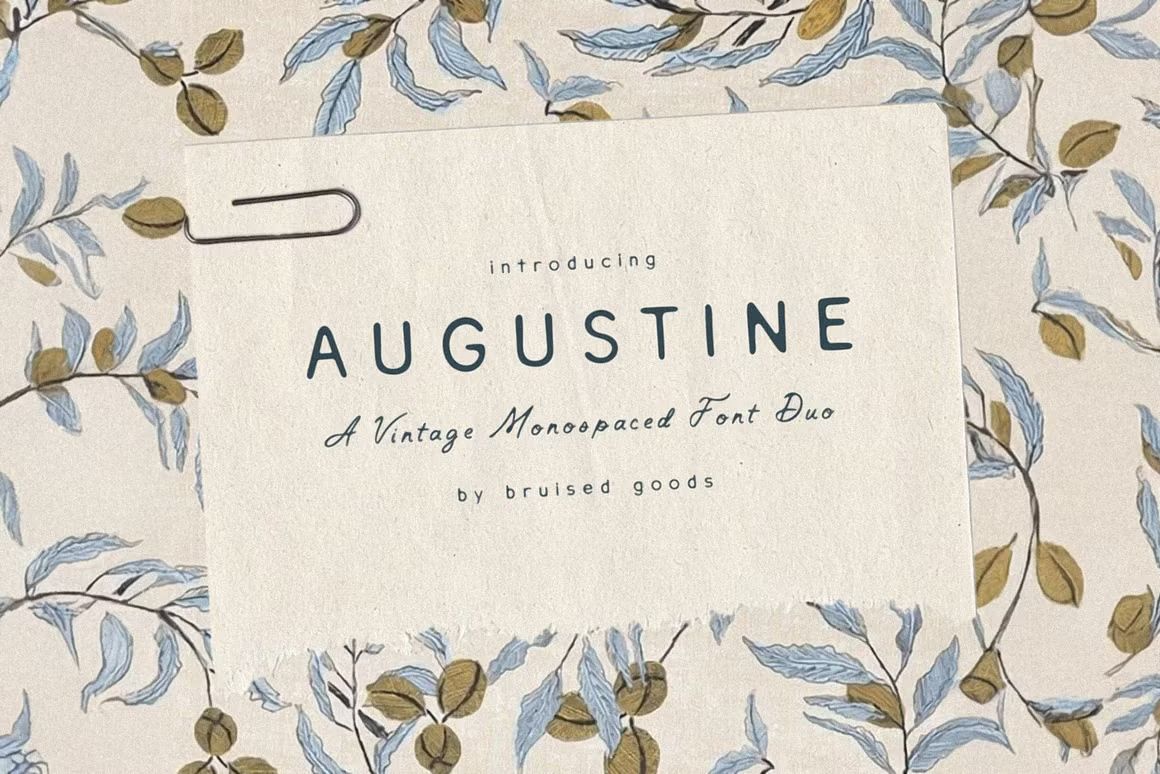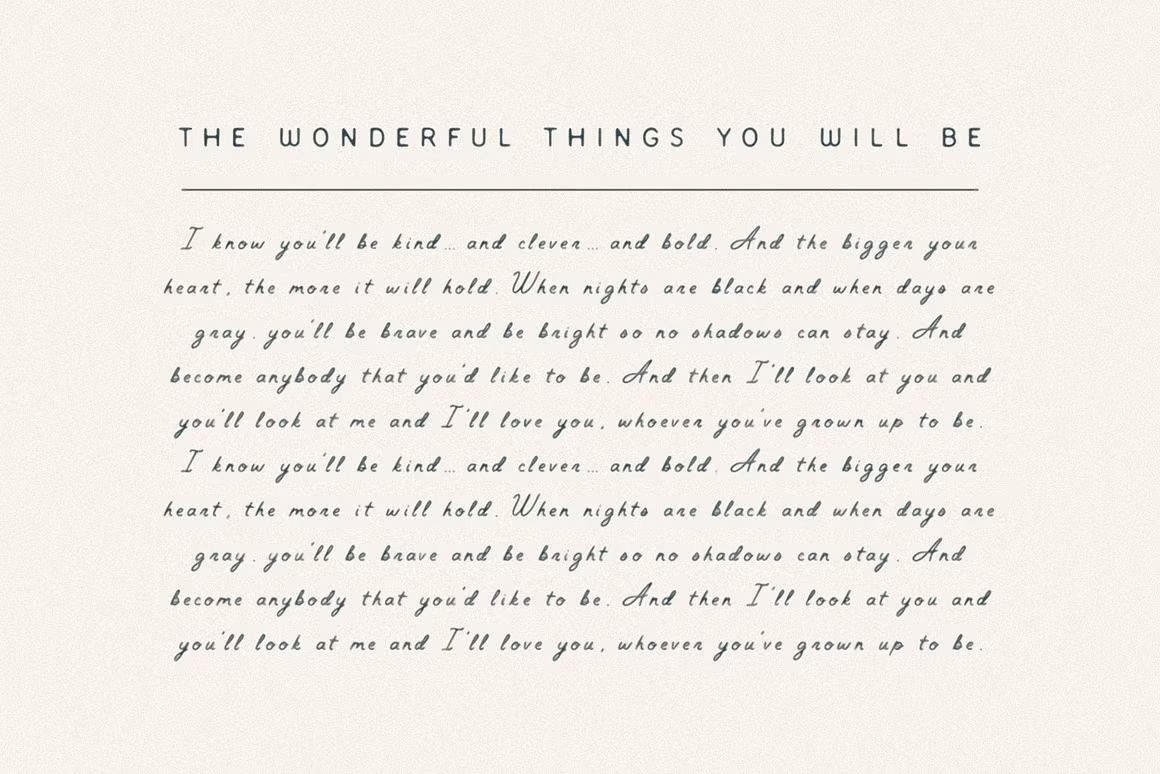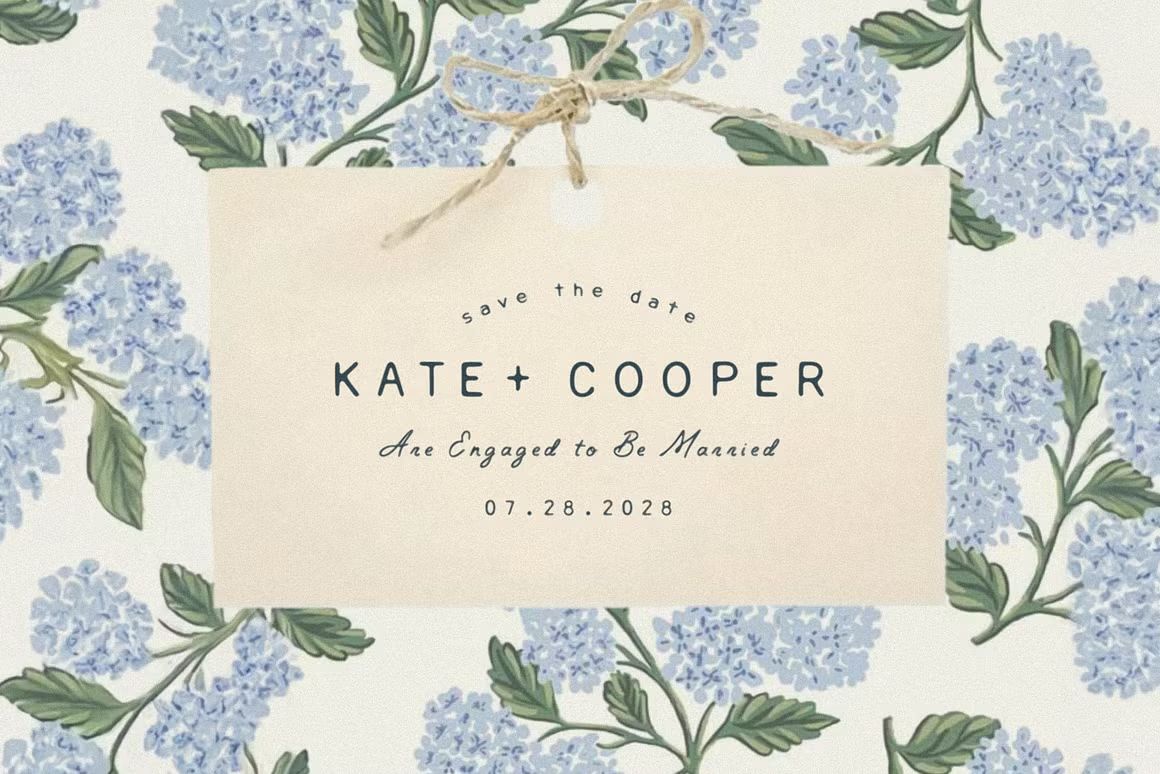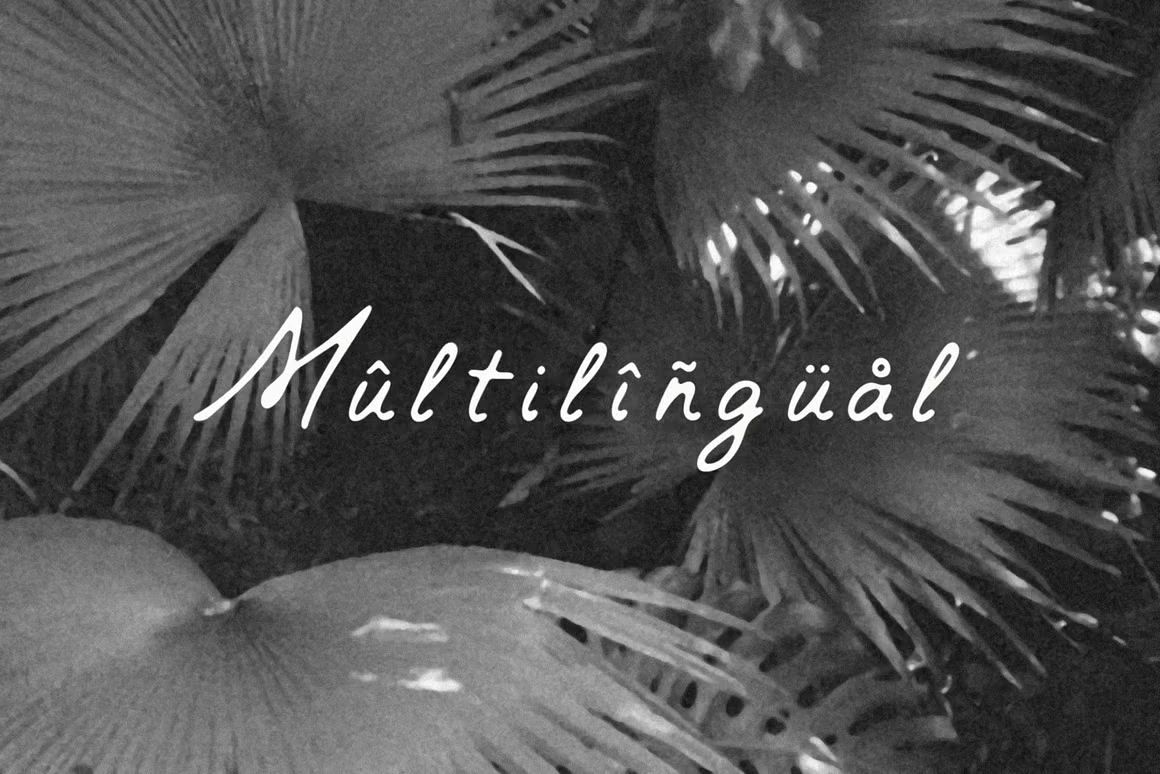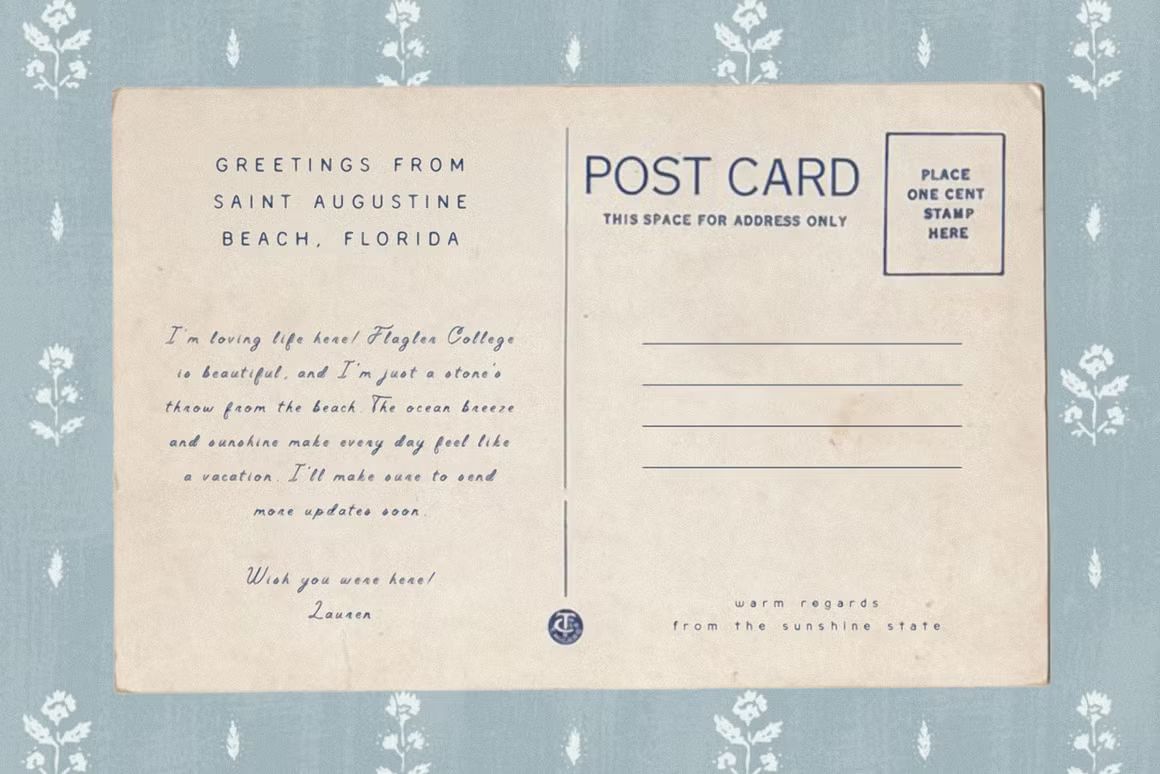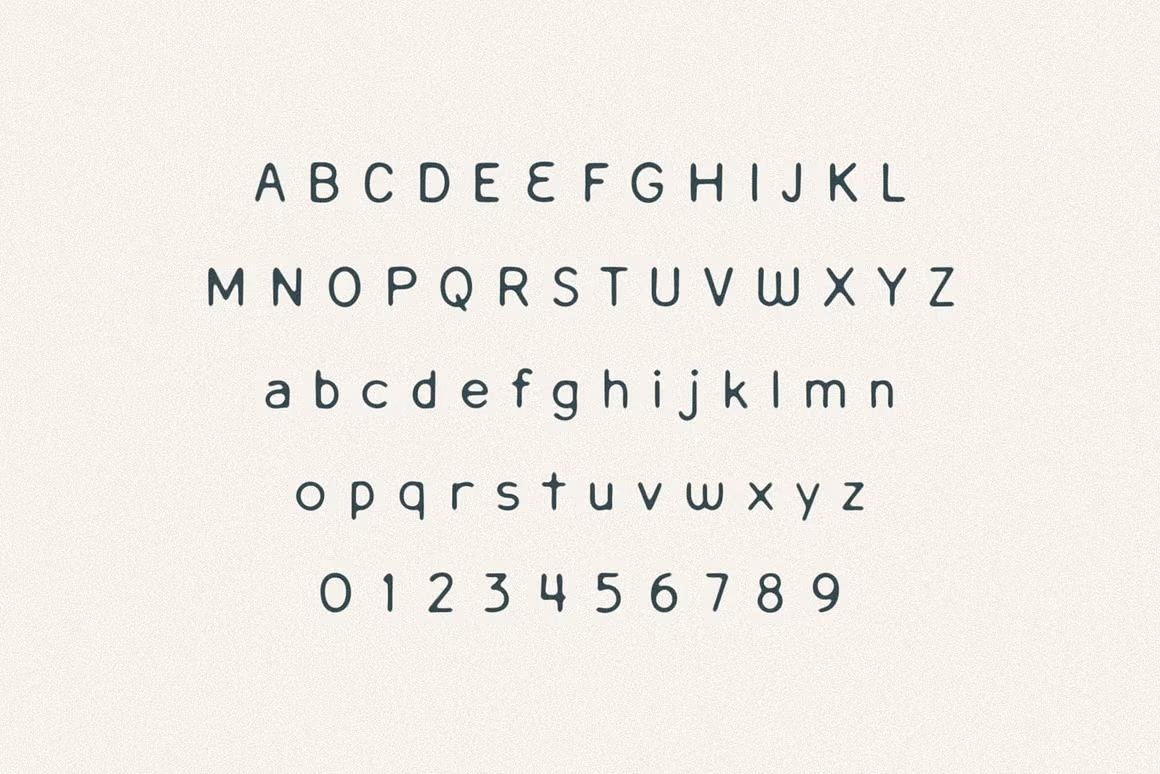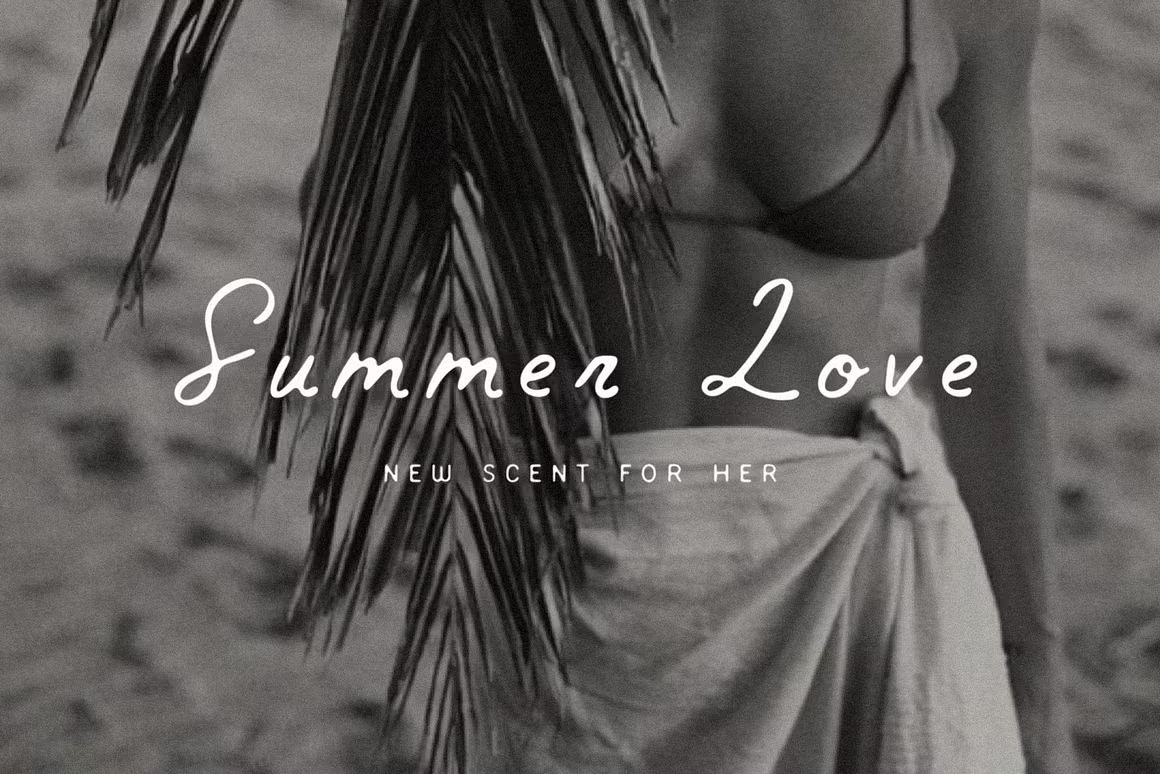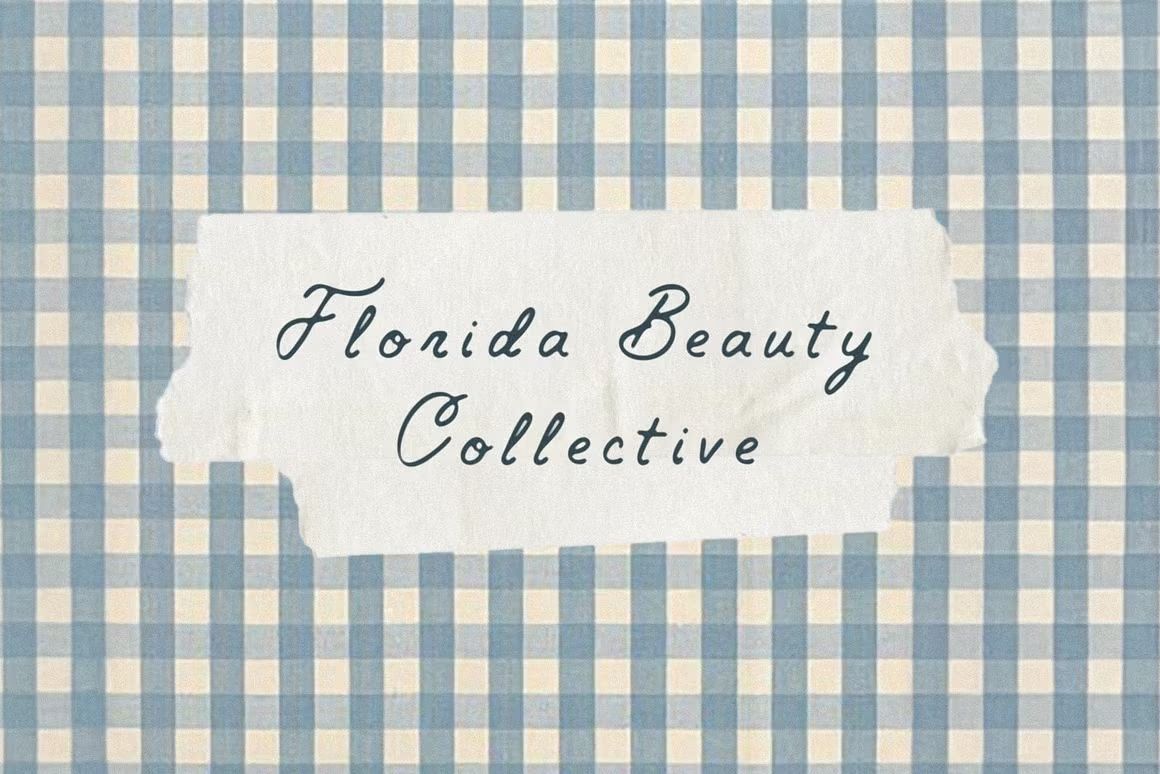
Augustine – Sans Serif Font
Augustine adalah font sans serif modern dengan garis-garis bersih dan proporsi seimbang, ideal untuk desain profesional, branding, logo, dan proyek yang membutuhkan tampilan minimalis dan elegan.
Augustine adalah font sans serif yang menggabungkan desain modern dan elegan dengan garis bersih dan proporsi yang seimbang. Didesain untuk memberikan kesan minimalis namun tetap profesional, font ini sangat cocok untuk branding, logo, editorial, dan desain visual lainnya yang membutuhkan tampilan yang sleek dan contemporary.
• Gaya sans serif modern dengan proporsi seimbang
• Cocok untuk branding, logo, editorial, dan desain profesional
• Termasuk huruf besar, huruf kecil, angka, dan simbol lengkap
• Ideal untuk proyek cetak maupun digital yang membutuhkan tampilan minimalis dan elegan